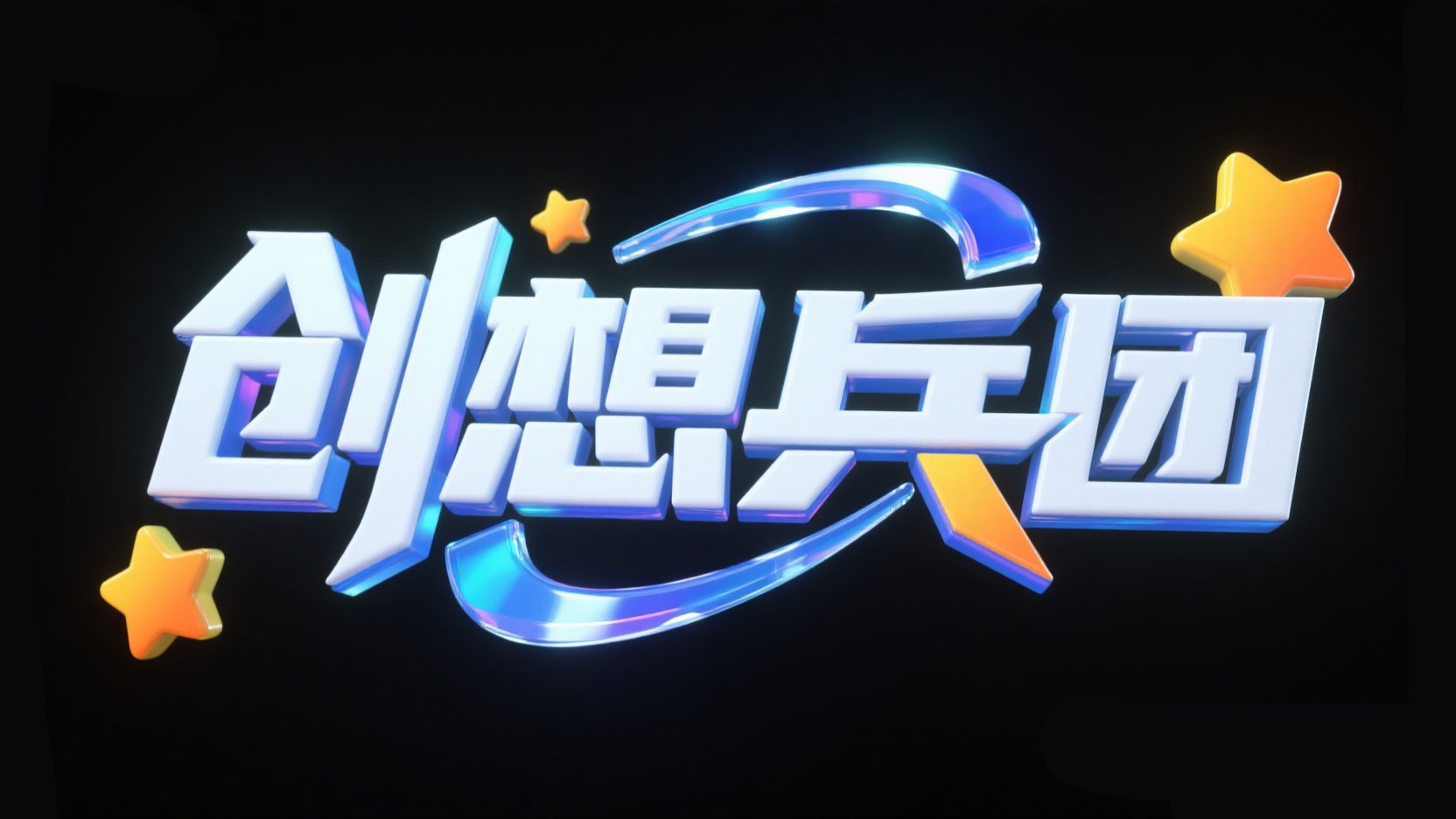
创作一个卡通科幻艺术字“创想兵团”,采用蓝白水...
创作一个卡通科幻艺术字“创想兵团”,采用蓝白水...AI字体提示词
风格定位
适合做风格探索与字形灵感延展。
适合场景
海报设计、品牌标题、电商设计、创意视觉
创作一个卡通科幻艺术字“创想兵团”,采用蓝白水晶渐变,笔画硬朗饱满带高光;“创” 字笔画呈螺旋纹变形,标题搭配黄橙渐变星星,与字体层叠穿插,突出童趣科幻的创意氛围。字体与元素形成一个整体且为正视图,背景为干净的黑色。
金属纸张肌理浮雕高对比立体阴影强笔触采用蓝白水晶渐变与字体层叠穿插